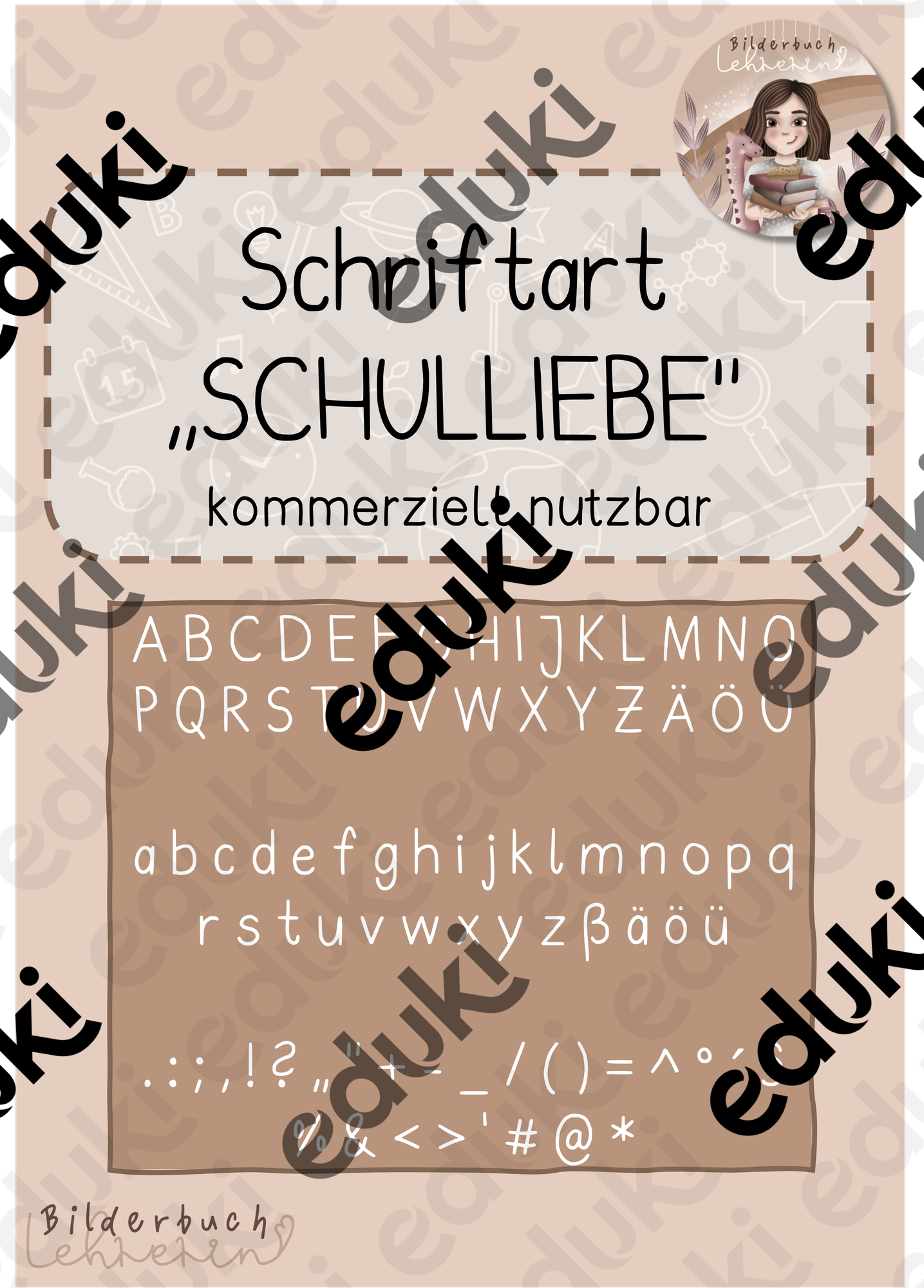
Diese Schriftart kannst du zu vielerlei Zwecken nutzen. Sie orientiert sich an einer sehr geradlinigen Handschrift. Meine Schrift darf zu privaten und auch kommerziellen Zwecken genutzt werden.
Schriftart: Schulliebe